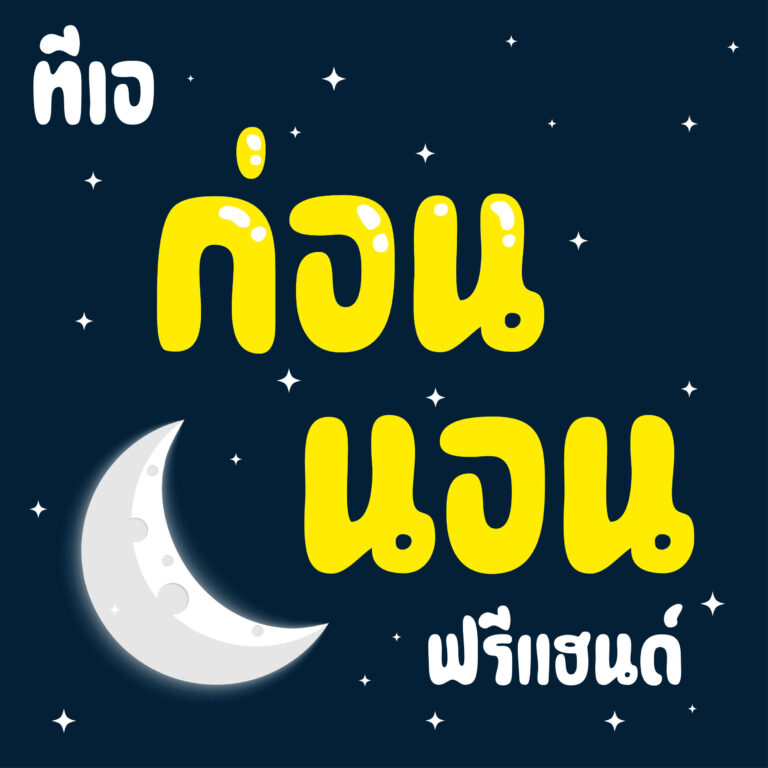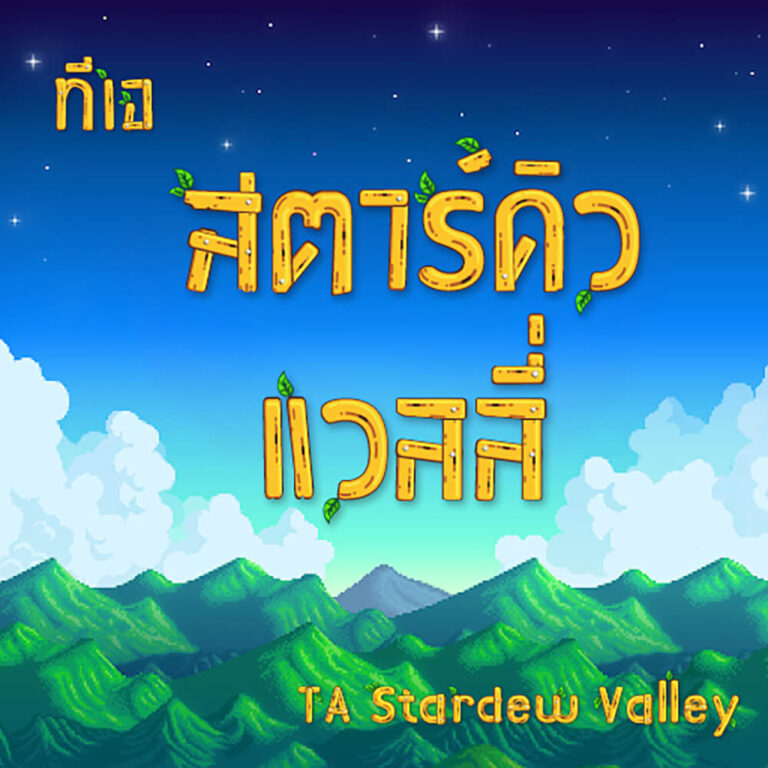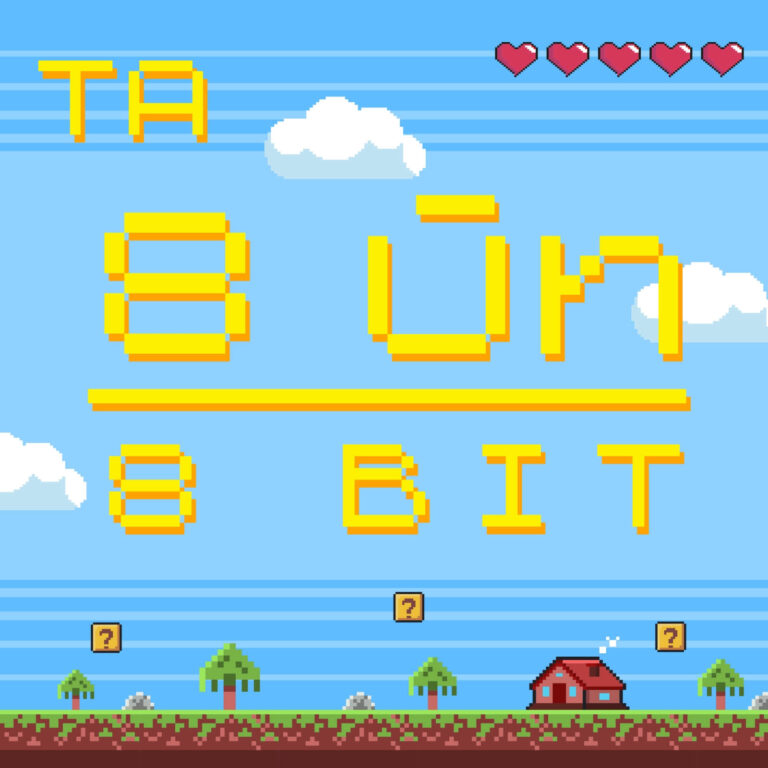
TA Font
สร้างสรรค์ฟอนต์ไว้ทั้งหมด 17 ตัว
ทีเอ ลูกโหนด (TA Look Node)
ฟอนต์นี้ไอเดียเริ่มต้นมาจากการเขียนปกรายงานสมัยมัธยมของผมเอง สมัยนั้นเพื่อนๆ จะให้ช่วยเขียนปกรายงานให้ อารมณ์แบบรีบจะส่งแล้วเองเขียนได้ เขียนให้หน่อย 5555 ตอนนั้นผมก็จะเขียนตัวหนังสือยาวๆ โย่งๆ แบบนี้ แต่ใช้ปากกาเส้นเล็กเขียนแล้วมันเห็นไม่ชัดก็เลยต้องทำลูกเล่นปลายหางให้บวมๆ คล้ายแบบฟอนต์ตัวนี้
ทีเอ เบลด (TA BLADE)
ฟอนต์ ทีเอ เบลด เป็นฟอนต์ที่อยากลองทำฟอนต์ ตัวหนาๆ คมๆ เท่ๆ ได้อารมณ์แบบปลายใบมีดคัตเตอร์ ตัดเฉียงพอว่างๆ ก็เลยไปขึ้นแบบของฟอนต์บนเว็บ fontstruct.com จนได้ฟอนต์ตัวนี้ขึ้นมา สุดท้ายก็เอามาจบงานใน FL7 ครับ
ทีเอ ปะปลาย (TA PaPlai)
เป็นฟอนต์ที่เริ่มจากความอยากทำฟอนต์เส้นประ เน้นสไตล์มากๆ หน่อย ก็ลองขีดๆ เขียนๆ แล้วเอามาดราฟต์ใน Adobe Illustrator แล้วมาทำเป็นฟอนต์ออกมาได้ 3 สไตล์ เอามาแจกให้ทดลองใช้ 1 สไตล์ สำหรับผู้สนับสนุนจะได้ฟอนต์ทั้ง 3 สไตล์ สามารถนำไปใช้เชิงพาณิชย์ได้ครับ
ทีเอ ยิปปี้ นิว เยียร์ (TA Yippy New Year)
ฟอนต์นี้ ไอเดียเริ่มต้นมาจากอยากทำฟอนต์ที่มีความยืดๆ หยุ่นๆ คล้ายๆ ฟอนต์แนวฮิปปี้ของต่างประเทศ แต่อยากให้ดูสนุกกว่า ก็ลองๆ ร่าง ลองๆ ออกแบบดู สุดท้ายก็ได้ออกมาประมาณนี้ ได้ทั้งความฮิปปี้ ทั้งสนุกสนานไปด้วยในตัว
ทีเอ อาฆาต (TA AKHA)
ฟอนต์ ทีเอ อาฆาต เป็นฟอนต์แนวสยองขวัญ เตรียมต้อนรับฮัลโลวีนกันสักหน่อย ไอเดียเริ่มต้นมาจากการ์ตูนผีเล่มละ 1 บาท ในสมัยก่อน ซึ่งยุคนี้ไม่ค่อยเห็นแล้ว แต่ตอนเด็กชอบอ่าน พอมาย้อนหาดูก็พบว่าตัวชื่อหนังสือผียุคนั้นสวยๆ ทั้งนั้น
ทีเอ ไฉไล พิกเซล ฟอนต์ (TA Chai Lai_Pixel)
ไอเดียเริ่มต้นฟอนต์ตัวนี้มาจากไปเห็นฟอนต์แนวไฮไลต์พิกเซลของต่างชาติมาแล้วชอบ เลยอยากทำฟอนต์แนวนี้เป็นภาษาไทยบ้าง ก็เลยไปขึ้นแบบฟอนต์จากเว็บ fontstruct.com แล้วเอามาปรับรายละเอียดในฟอนต์แล็บอีกทีครับ
ทีเอ ทิคแทคโท (TA TicTacTo)
เป็นฟอนต์ที่อยากทำฟอนต์ตัวหนาๆ แท่งๆ โดยใช้ภาพจำมาจากหนังสือการ์ตูนเวลามีฉากแอคชัน หรือเสียงดัง จะใช้ตัวหนังสือแท่งๆ เหลี่ยมๆ แทนเสียง แล้วก็ลองขึ้นแบบใน Adobe Illustrator ก็ได้ออกมาประมาณนี้
ทีเอ 8 บิท (TA 8 BIT)
เป็นฟอนต์ที่ผมทำไว้นานมากแล้วนะครับ ตอนนั้นทำมาทดสอบเกม แล้วก็ไม่ได้ใช้ต่ออีกเลย ระยะหลังๆ ผมไม่ค่อยว่างทำฟอนต์ จึงลืมไปว่าทำฟอนต์ตัวนี้ไว้ ช่วงนี้ผมพยายามแบ่งเวลาหลังเลิกงานประจำกลับมานั่งทำทั้งงานฟอนต์และงานออกแบบ จึงค้นไปเจอไฟล์ฟอนต์ตัวนี้เลยคิดว่าเอามาแจกฟรี น่าจะเกิดประโยชน์ได้มากกว่าเก็บไว้เฉยๆ
ทีเอ เกมบอย (TA Game Boy)
ฟอนต์ ทีเอ เกมบอย / TA Game Boy Font เป็นฟอนต์แนวพิกเซล ที่ได้แรงบันดาลใจจากในตอนวัยเด็กชอบเล่นเกมบอย แล้วจะเห็นฟอนต์นี้ตอนเปิดเครื่องเกมทุกครั้ง จึงไปหารูปแบบเก่าๆ ของฟอนต์ตัวนี้จากเว็บ แล้วนำมาต่อยอดเป็นฟอนต์ไทยสไตล์พิกเซลเต็มตัว
ทีเอ สตาร์ดิว วัลเลย์ คัลเลอร์ (TA Stardew Valley Color)
ห่างหายไปนานกับการลงฟอนต์ เนื่องจากภารกิจในชีวิตมากมายเหลือเกิน ฟอนต์ ทีเอ สตาร์ดิว วัลเลย์ เป็นการทดลองทำฟอนต์สีตัวแรกของผมนะครับ โดยไอเดียเริ่มต้นมาจากเกม Stardew Valley เกมแนวปลูกผัก ทำสวน ที่สายเกมน่าจะรู้จักกันดี
ทีเอ จู๊ด จู๊ด ฟรีแฮนด์ (TA JuudJuud Freehand)
เป็นฟอนต์แนวทดลองที่ผมเองอยากลองเอาจุดกลมๆ ไปวางไว้ที่ปลายเส้นของตัวหนังสือภาษาไทยดูก็ได้ออกมาเป็นแบบนี้ ดูแปลกตาดี อ่านยากนิดหน่อย แต่ก็รู้สึกว่าน่าสนใจดี ชวนให้นึกถึงเกมลากเส้นต่อจุดสมัยเด็กๆ
ทีเอ ๑๖​ บิต (TA 16 Bit)
เป็นฟอนต์แนวเกมพิกเซล เรโทร ย้อนยุค นะครับ ฟอนต์นี้น่าจะถูกใจสายเกมยุคเก่าๆ หน่อย โดยผมเริ่มต้นทำตัวฟอนต์จากเว็บ fontstruct.com นะครับ เสร็จแล้วจึงเซฟมาทำงานต่อในโปรแกรมทำฟอนต์อีกที
ทีเอ ลัลลาบาย (TA Lullaby)
เป็นฟอนต์แนวปลายตัดโค้ง ที่ผมทดลองเล่นลูกเล่นกับการสะบัดของหางให้ตัวหนังสือมีการเชื่อมต่อกันนะครับแต่เพื่อให้อ่านง่ายและใช้งานได้หลากหลายขึ้น จึงทำฟอนต์นี้แบบไม่เล่นหางออกมาอีกแบบด้วยจึงได้ฟอนต์ออกมา 2 แบบ คือ TA lullaby LS ตัวเล่นหาง กับ TA Lullaby NM ตัวไม่มีหาง
ทีเอ ลำดวน (ซัมเมอร์)
ฟอนต์นี้เริ่มจาก อยากทำฟอนต์ที่ได้อารมณ์ทะเล, ฤดูร้อน, ปาร์ตี้ชายหาด จึงลองๆ ไปหาฟอนต์แนวทางของต่างประเทศดูหลายๆ แบบ แล้วลองเอามาทำ เป็นตัวอักษรไทยดู ทำไปทำมา ก็ได้ตัวอักษรม้วนๆ แบบนี้ ดูๆ ไปก็สนุกดี
ทีเอ ก่อนนอน ฟรีแฮนด์ (TA GonNon)
เป็นฟอนต์ลายมือ สไตล์น่ารัก เด็กๆ ที่ผมเขียนขึ้นเองนะครับชื่อ ฟอนต์ ก่อนนอน มาจากที่ผมใช้เวลาก่อนนอนทำทุกๆ คืน ทำจนง่วงจนหลับไปเลยครับ
ทีเอ แมกกาซีน (TA Magazine)
เป็นฟอนต์ที่เล่นกับน้ำหนัก หนา-บาง ของเส้นนะครับ ไอเดียเริ่มต้นมาจากฟอนต์ของต่างประเทศ ชื่อ Magazine เห็นแล้วรู้สึกชอบการเล่นกับน้ำหนัก จึงลองๆ วางเส้นหนักเบาสลับๆ เป็นภาษาไทยดู ก็ได้ออกมาประมาณนี้ ในอนาคตว่าจะลองใส่หัวกลม หัวทึบ เพิ่มเติมเป็นฟอนต์ตัวต่อๆ ไปนะครับ